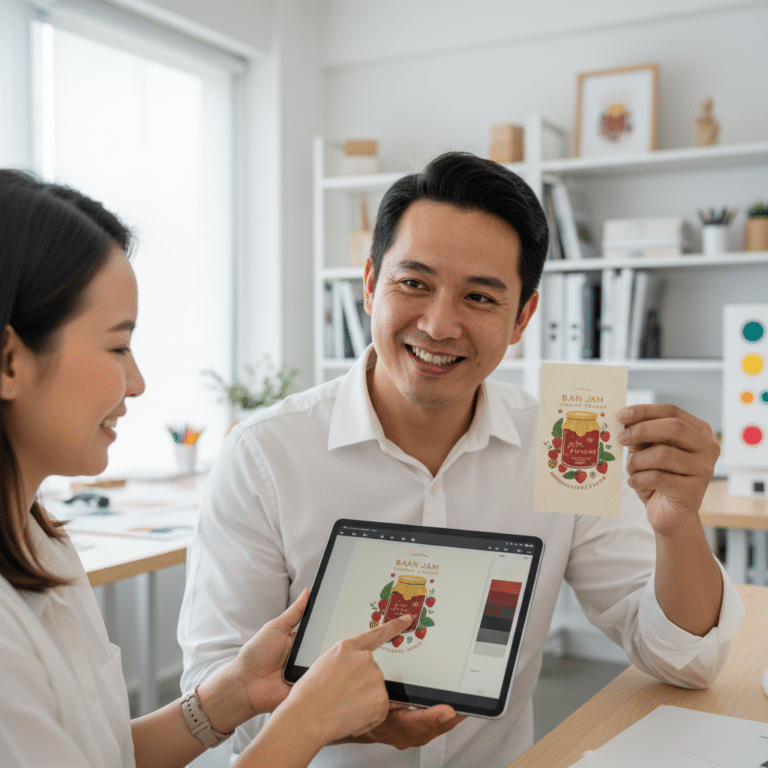
เทคนิคเลือกฟอนต์ป้ายร้าน-สติ๊กเกอร์ ให้อ่านง่าย ขายดี!
การเลือกฟอนต์สำหรับป้ายร้านหรือสติ๊กเกอร์ฉลากสินค้าไม่ใช่แค่เรื่องของความสวยงาม แต่เป็นองค์ประกอบสำคัญที่ส่งผลโดยตรงต่อการรับรู้ของลูกค้าและยอดขาย การเรียนรู้ เทคนิคเลือกฟอนต์ป้ายร้าน-สติ๊กเกอร์ ให้อ่านง่าย ขายดี! จึงเป็นทักษะที่ผู้ประกอบการ SME ไม่ควรมองข้าม เพราะฟอนต์ที่เหมาะสมสามารถสื่อสารบุคลิกของแบรนด์ สร้างความน่าเชื่อถือ และดึงดูดสายตาให้ลูกค้าตัดสินใจซื้อได้ในที่สุด
สรุปประเด็นสำคัญเพื่อการออกแบบที่โดดเด่น
- ความสอดคล้องกับแบรนด์: ฟอนต์ต้องสะท้อนตัวตนและบุคลิกของธุรกิจได้อย่างชัดเจน ไม่ว่าจะเป็นความคลาสสิก ทันสมัย เป็นกันเอง หรือหรูหรา
- การอ่านง่ายต้องมาก่อน: ความสวยงามของฟอนต์จะไร้ความหมายหากลูกค้าไม่สามารถอ่านข้อความได้อย่างรวดเร็วและชัดเจน โดยเฉพาะจากระยะไกลหรือบนบรรจุภัณฑ์ขนาดเล็ก
- ความเรียบง่ายคือหัวใจ: การใช้ฟอนต์จำนวนน้อย (ไม่เกิน 2-3 แบบ) จะช่วยให้งานออกแบบดูสะอาดตา เป็นมืออาชีพ และไม่สร้างความสับสนให้กับผู้พบเห็น
- สร้างการรับรู้ด้วยลำดับชั้น: การใช้น้ำหนัก (ความหนา-บาง) ขนาด และสีของฟอนต์อย่างมีกลยุทธ์ ช่วยนำสายตาของลูกค้าไปยังข้อมูลที่สำคัญที่สุดก่อน เช่น ชื่อแบรนด์ โปรโมชั่น หรือจุดเด่นของสินค้า
- จัดสรรพื้นที่ว่างอย่างเหมาะสม: การเว้นระยะรอบตัวอักษรและองค์ประกอบต่างๆ (White Space) ช่วยให้ป้ายหรือสติ๊กเกอร์ดูไม่แออัด สบายตา และยกระดับภาพลักษณ์ของแบรนด์ให้ดูพรีเมียมขึ้น
ทำไมฟอนต์จึงเป็นหัวใจสำคัญของการออกแบบแบรนด์ SME
ในโลกธุรกิจที่มีการแข่งขันสูง การสร้างความแตกต่างและเป็นที่จดจำเป็นสิ่งสำคัญ ฟอนต์ (Font) หรือรูปแบบตัวอักษร คือเครื่องมือสื่อสารที่ทรงพลังซึ่งทำงานเงียบๆ เบื้องหลังโลโก้และสีสันของแบรนด์ มันไม่ใช่เพียงแค่ตัวอักษรที่เรียงกันเป็นคำ แต่เป็น “น้ำเสียง” ของแบรนด์ที่สื่อสารกับลูกค้าโดยไม่ต้องเอ่ยคำพูด
สำหรับธุรกิจ SME การออกแบบป้ายร้าน ป้ายโฆษณา หรือสติ๊กเกอร์ฉลากสินค้า ถือเป็นการลงทุนที่ต้องให้ความสำคัญ เพราะสื่อเหล่านี้คือด่านแรกที่ลูกค้าจะได้สัมผัสกับแบรนด์ ฟอนต์ที่เลือกใช้จะส่งผลต่อการรับรู้ในทันที เช่น ฟอนต์ที่มีลักษณะโค้งมนอาจให้ความรู้สึกเป็นมิตรและเข้าถึงง่าย เหมาะกับร้านกาแฟหรือสินค้าสำหรับเด็ก ในขณะที่ฟอนต์ที่มีเส้นตรง คมชัด อาจสื่อถึงความเป็นทางการ ความน่าเชื่อถือ และความทันสมัย เหมาะกับธุรกิจเทคโนโลยีหรือคลินิกเสริมความงาม การเลือกฟอนต์ที่ผิดพลาดอาจส่งผลให้แบรนด์ถูกเข้าใจผิด หรือที่แย่กว่านั้นคือถูกมองข้ามไปเลย ดังนั้น การทำความเข้าใจหลักการเลือกฟอนต์จึงเป็นก้าวแรกสู่การสร้างแบรนด์ที่แข็งแกร่งและประสบความสำเร็จ
หลักการพื้นฐาน: เทคนิคเลือกฟอนต์ป้ายร้าน-สติ๊กเกอร์ ให้อ่านง่าย ขายดี!
การเลือกฟอนต์ที่มีประสิทธิภาพต้องอาศัยการผสมผสานระหว่างศาสตร์และศิลป์ โดยคำนึงถึงความสมดุลระหว่างความสวยงาม การสื่อสาร และการใช้งานจริง หลักการต่อไปนี้เป็นพื้นฐานสำคัญที่จะช่วยให้การออกแบบป้ายและสติ๊กเกอร์ของคุณโดดเด่นและทำหน้าที่ได้อย่างเต็มศักยภาพ
1. เลือกฟอนต์ที่สะท้อนบุคลิกของแบรนด์ (Brand Personality)
ก่อนจะเลือกฟอนต์ใดๆ ต้องตอบคำถามให้ได้ก่อนว่า “แบรนด์ของเรามีบุคลิกแบบไหน?” ฟอนต์แต่ละตระกูลมีความสามารถในการสื่อสารอารมณ์และความรู้สึกที่แตกต่างกันออกไป:
- ฟอนต์แบบมีเชิง (Serif): ฟอนต์กลุ่มนี้จะมี “ขีด” หรือ “เชิง” เล็กๆ ที่ปลายตัวอักษร ให้ความรู้สึกคลาสสิก, ดั้งเดิม, น่าเชื่อถือ, และมั่นคง เหมาะสำหรับธุรกิจที่ต้องการสร้างภาพลักษณ์ที่ดูเป็นทางการและมีประวัติศาสตร์ยาวนาน เช่น สำนักงานกฎหมาย, ร้านอาหารหรู, หรือแบรนด์สินค้าออร์แกนิกที่เน้นความเป็นธรรมชาติ
- ฟอนต์แบบไม่มีเชิง (Sans Serif): เป็นฟอนต์ที่ไม่มีขีดที่ปลายตัวอักษร มีลักษณะเรียบง่าย ทันสมัย และสะอาดตา อ่านง่ายในทุกขนาด จึงเป็นที่นิยมอย่างสูงในปัจจุบัน เหมาะสำหรับธุรกิจที่ต้องการสื่อถึงความทันสมัย, เทคโนโลยี, ความเป็นมิตร และเข้าถึงง่าย เช่น ร้านค้าปลีก, สตาร์ทอัพเทคโนโลยี, หรือแบรนด์แฟชั่น
- ฟอนต์ลายมือหรือฟอนต์ตกแต่ง (Script/Decorative): ฟอนต์กลุ่มนี้มีลักษณะเฉพาะตัวสูง อาจดูเหมือนลายมือเขียนหรือมีการออกแบบที่วิจิตรเป็นพิเศษ สามารถให้ความรู้สึกอบอุ่น, เป็นกันเอง, สร้างสรรค์, หรือหรูหราได้ แต่เนื่องจากอ่านยากกว่าฟอนต์ประเภทอื่น จึงมักใช้กับข้อความสั้นๆ ที่เป็นหัวเรื่อง หรือชื่อแบรนด์ เพื่อสร้างจุดเด่น ไม่เหมาะกับข้อความยาวๆ หรือข้อมูลสำคัญ
2. ให้ความสำคัญกับความชัดเจนและการอ่านง่าย (Readability First)
นี่คือหลักการที่สำคัญที่สุด ฟอนต์ที่สวยงามที่สุดในโลกก็ไร้ประโยชน์หากลูกค้าไม่สามารถอ่านข้อความบนป้ายหรือสติ๊กเกอร์ของคุณได้ ความสามารถในการอ่าน (Readability) ขึ้นอยู่กับหลายปัจจัย:
- การมองเห็นจากระยะไกล: สำหรับป้ายร้านค้าหรือป้ายไวนิล ลูกค้าต้องสามารถอ่านชื่อร้านและข้อมูลสำคัญได้จากระยะไกล ฟอนต์ที่มีเส้นหนาและชัดเจนจะทำงานได้ดีกว่า
- ขนาดที่เล็ก: สำหรับสติ๊กเกอร์ฉลากสินค้า ซึ่งมีพื้นที่จำกัด ฟอนต์ต้องยังคงอ่านออกได้ง่ายแม้จะมีขนาดเล็ก ควรหลีกเลี่ยงฟอนต์ที่มีรายละเอียดซับซ้อนมากเกินไป